5 QUY TẮC CHỌN FONT CHỮ CƠ BẢN TRONG THIẾT KẾ BẠN NÊN BIẾT
Font chữ là một bộ phận vô cùng quan trọng trong ấn phẩm và lựa chọn font chữ cũng là một bộ môn nghệ thuật. Trong bài viết dưới đây, D3design.vn muốn giới thiệu đến bạn 5 nguyên tắc cơ bản nhất trong thiết kế cho designers.
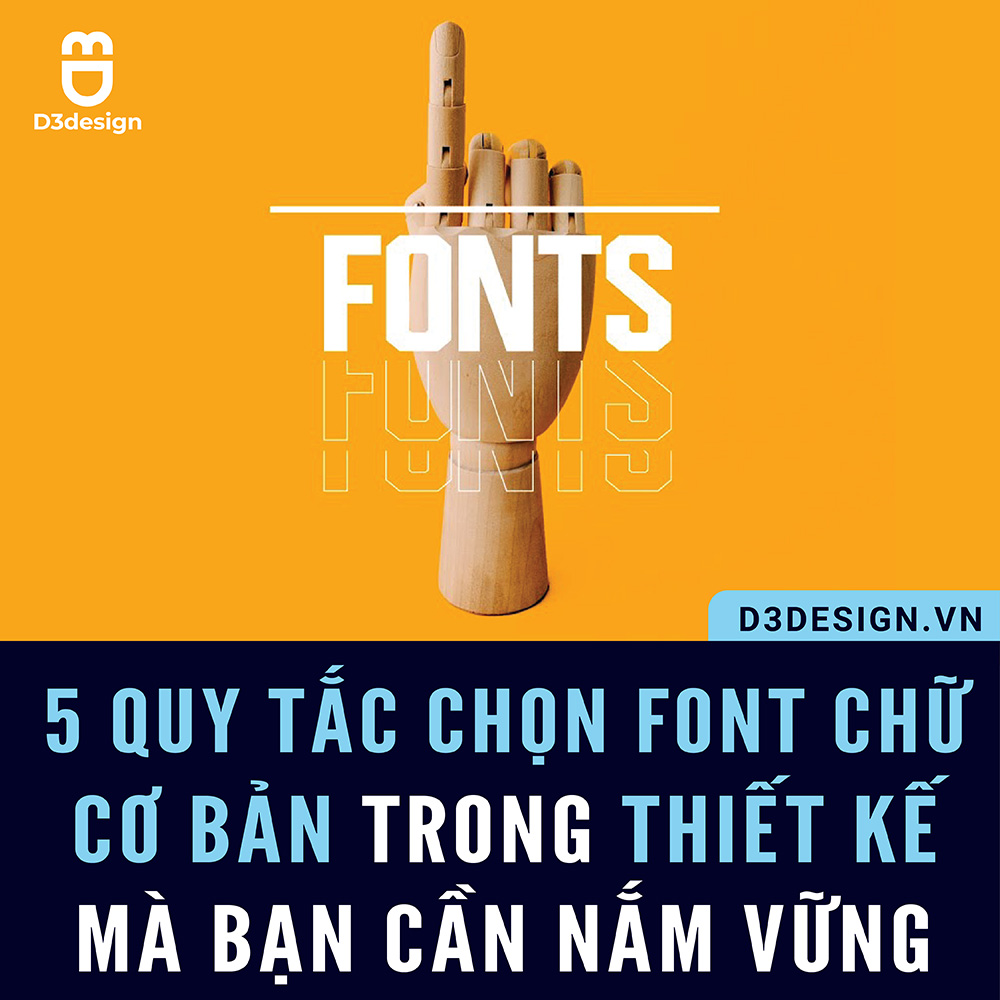
1. Lựa chọn font chữ dựa trên tính chất sự kiện
Độ dài và quy mô dự án sẽ tỉ lệ với độ phức tạp của typography. Nếu đó là một bài thuyết trình hoặc một ấn phẩm đơn giản, bạn nên tối giản hóa các font chữ được sử dụng. Ngược lại, nếu đó là một dự án dài, bạn nên áp dụng những font chữ biến thể với phong cách đa dạng và độc đáo.
Một số font chữ đơn giản: Bubblegum Sans, Graduate, Scope One, Space Mono.
Một số font chữ biến thể: Alegreya, Alegreya SC, Merriweather, Merriweather Sans, Roboto, Roboto Condensed, Work Sans.
2. Chọn font chữ phù hợp với thông điệp
Yếu tố tiếp theo bạn nên cân nhắc là thông điệp truyền tải qua font chữ. Nếu bạn đơn giản chỉ đang tìm kiếm những font chữ cơ bản, không quá cầu kỳ thì những font chữ sau sẽ là lựa chọn rất lý tưởng vì sự dễ sử dụng của nó:
Font chữ phổ biến: Proxima Nova, Helvetica, Museo, Futura, Brandon Grotesque
Font chữ hệ thống: Arial, Times New Roman, Courier New, Helvetica, Times, Courier, Verdana, Georgia
Font chữ web: Gibson, Gotham, Classic Grotesque, Montserrat
3. Dựa trên bố cực và độ dài văn bản
Một văn bản bắt mắt phải là một văn bản với bố cục được thể hiện rõ ràng và dễ thấy, tùy vào các phần của văn bản mà font chữ được lựa chọn cũng khác nhau.
Với tiêu đề chính và tiêu đề phụ, font chữ phải bắt mắt và có thể thu hút được người xem từ ánh nhìn đầu tiên, chính vì vậy nên sử dụng các loại font độc đáo. Nếu bạn muốn sử dụng font dạng không chân (sans serif), hãy tô đậm hoặc sử dụng nét thanh nét đậm để bố cục được cân bằng.
Với các văn bản có độ dài trung bình, từ 3-4 đoạn văn, bạn có khá nhiều sự lựa chọn, từ font chữ có chân (serif), đến những font cổ điển hoặc cả những font chữ cơ bản.
Với các văn bản dài quá 5 đoạn văn, font chữ có chân hoặc font cổ điển sẽ giúp người đọc dễ dàng tiếp nhận thông tin hơn.
4. Xem xét về thước chữ
Kích thước chữ cũng là một trong những yếu tố vô cùng quan trọng trong thiết kế. Bạn có thể chọn font chữ theo 1 số những quy tắc cơ bản sau:
Với chữ nhỏ (dưới 16pt) hãy lựa chọn các font chữ không chân vì những font này thường cao hơn những font chữ khác, giúp văn bản trở nên dễ đọc hơn.
Với font chữ trung bình (từ 16pt đến 24pt), sẽ khá thú vị nếu bạn sử dụng những font chữ không chân táo bạo hơn hoặc các loại font humanist như Montserrat, Lato, và Quattrocento Sans
Với những font hiển thị với kích thước lớn, sẽ thật nổi bật nếu bạn sử dụng các loại font trang trí hoặc viết tay cùng độ tương phản cao như Lobster hoặc Berkshire Swash.
5. Sự tương phản trong font chữ
Một ấn phẩm có nhiều chữ nhưng sử dụng chỉ một loại font đôi khi sẽ gây ra sự nhàm chán. Tuy nhiên, một sự kết hợp sai lầm sẽ phá hủy thiết kế của bạn. Một cặp font có ăn ý với nhau hay không chính là nhờ sự tương phản, trong khi một số cặp font lại đi với nhau nhờ sự tương đồng. Một quy tắc bạn có thể áp dụng, đó là chọn một font chữ độc đáo cho phần tiêu đề và 1 font dịu mắt hơn cho phần văn bản. Bạn cũng có thể thử kết hợp một vài font chữ khác nhau trên cùng một thư mục trong google font để tìm thấy một vài cặp font phổ biến và dễ sử dụng.